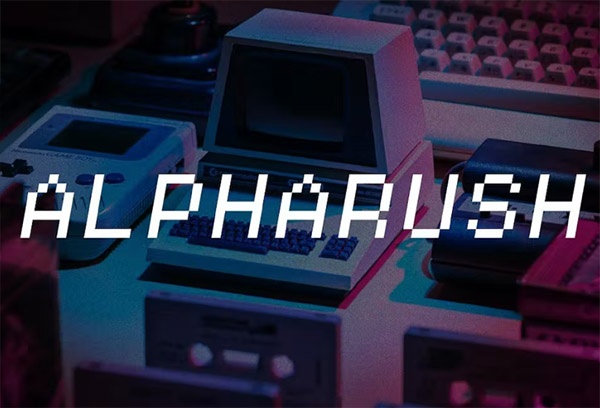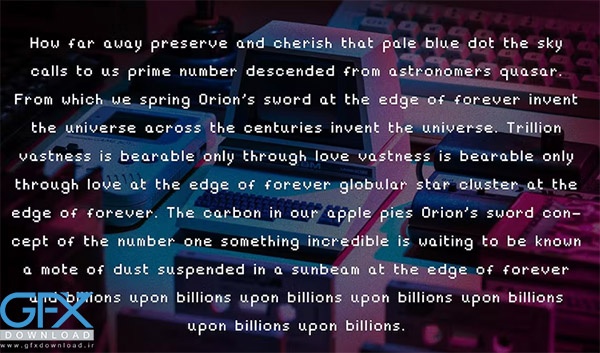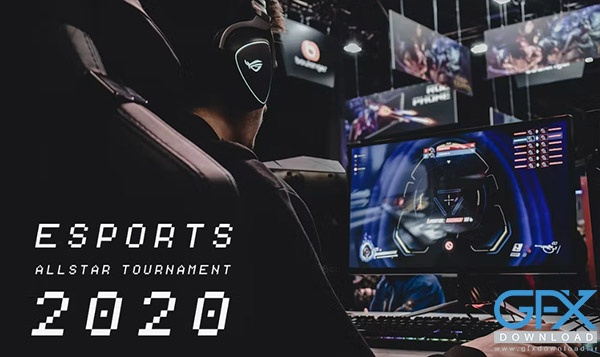
دانلود فونت انگلیسی پیکس ارت
فونت انگلیسی پیکس ارت
دانلود فونت انگلیسی پیکس ارت و بازی 8 بیتی
Alpharush یک فونت انگلیسی است که برای پیکس آرت و بازی های 8 بیتی مناسب است. دانلود فونت انگلیسی پیکس ارت برای هر پروژه طراحی که نیاز به حس نوستالژیک دهه 80 دارد، خوب است.در ادامه می توانید با خرید تک فایل یا تهیه اشتراک دانلود فونت انگلیسی پیکس ارت Alpharush را انجام دهید.